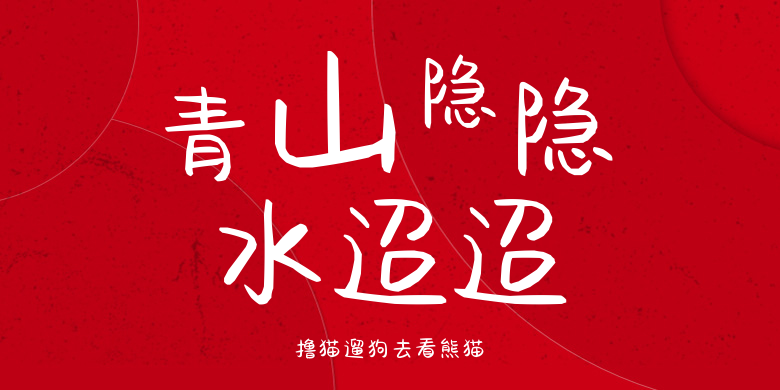
撸猫遛狗去看熊猫
撸猫遛狗去看熊猫,这款字体结构工整、笔画清晰,兼顾美观与易读性,适用于标题、正文、海报、包装、LOGO 等多种场景。字形优雅稳定,风格百搭耐看,适配日常排版与创意设计,让文字呈现更舒适、更具质感。撸猫遛狗去看熊猫一笔一画,皆是细节,以均衡的比例、流畅的线条打造舒适视觉体验,字形端正大气,风格简约现代。无论是商业设计、品牌宣传还是日常排版,都能轻松驾驭,让文字更有格调与力量。撸猫遛狗去看熊猫字体下载。